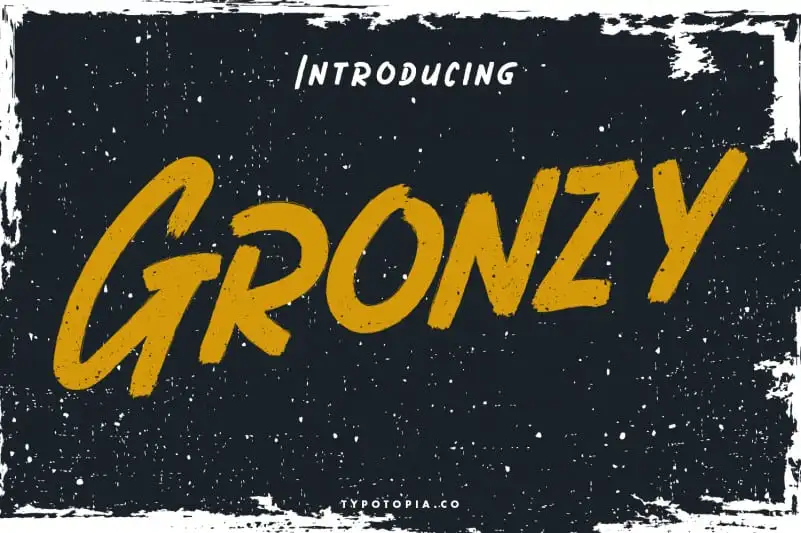
Gronzy Brush Font – Download Grátis
Introduzimos a Gronzy Brush Font neste formato de tipo com uma temática horrorosa, oferecendo-lhe estilo único. Esta nova adição à nossa gama de fuentes brush vem desenhada para criar um efeito poderoso e inovador no seu design gráfico. Ideal para aqueles que buscam um tom sombrio e intrigante em seus projetos visuais, a Gronzy Brush Font foi criada por tipoTopia, designer especializado em tipos de brinquedo. Ela incorpora elementos góticos e dark-horror nos traços da fórmula, permitindo que você faça um uso inovador desta fonte. A Gronzy Brush Font pode transformar um design simples em algo realmente assustador ou emocionante, dependendo do seu estilo. Tornando-a uma escolha ótima para designers de logos e marcas, ilustradores e criadores de conteúdo online que buscam uma fonte única e inovadora para seus trabalhos visuais. Se você procura uma fórmula visual poderosa para complementar o design do seu site ou aplicativo móvel, a Gronzy Brush Font é um excelente investimento. Ela proporcionará um toque assustador e moderno aos seus projetos sem comprometer o legível ou confiável funcionamento da letra.